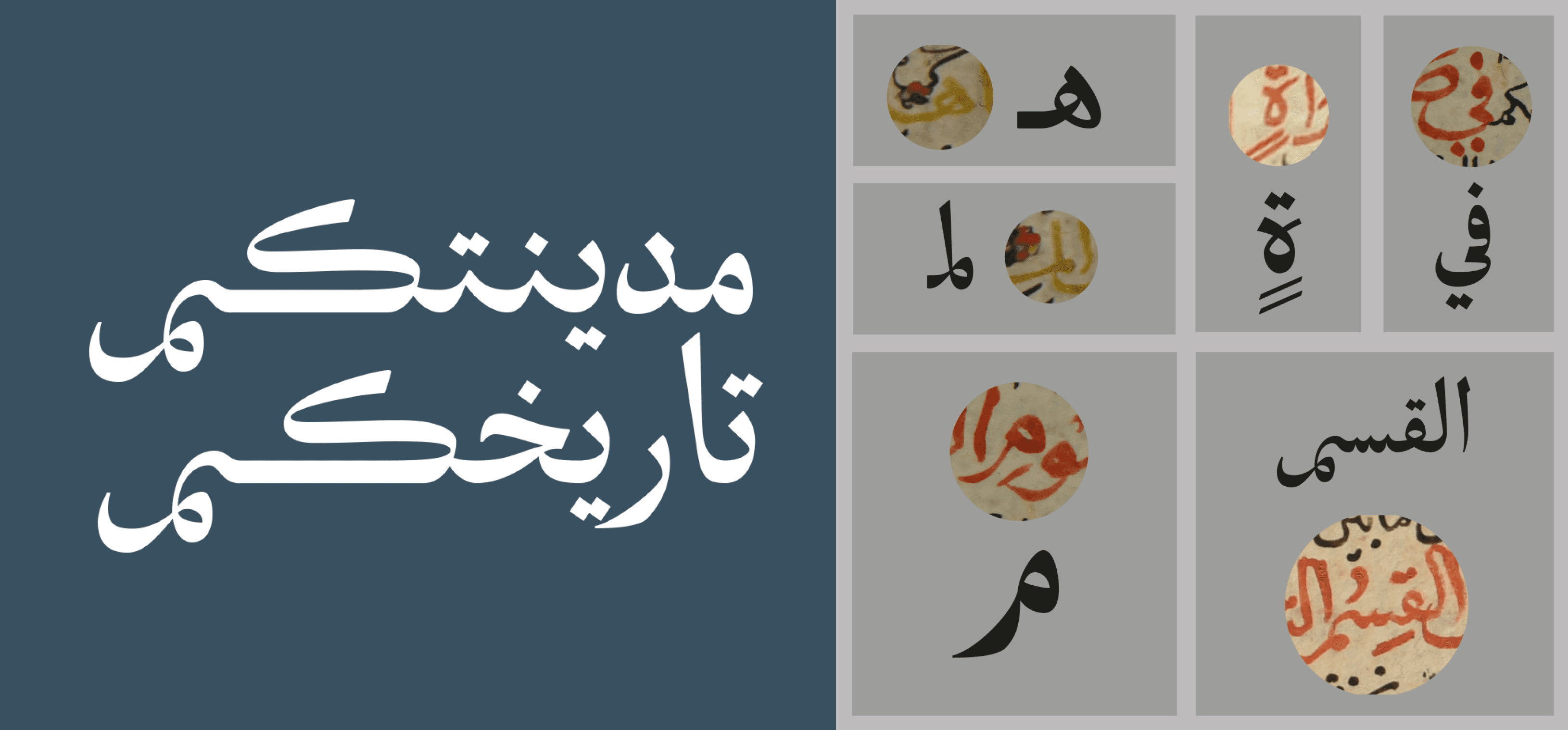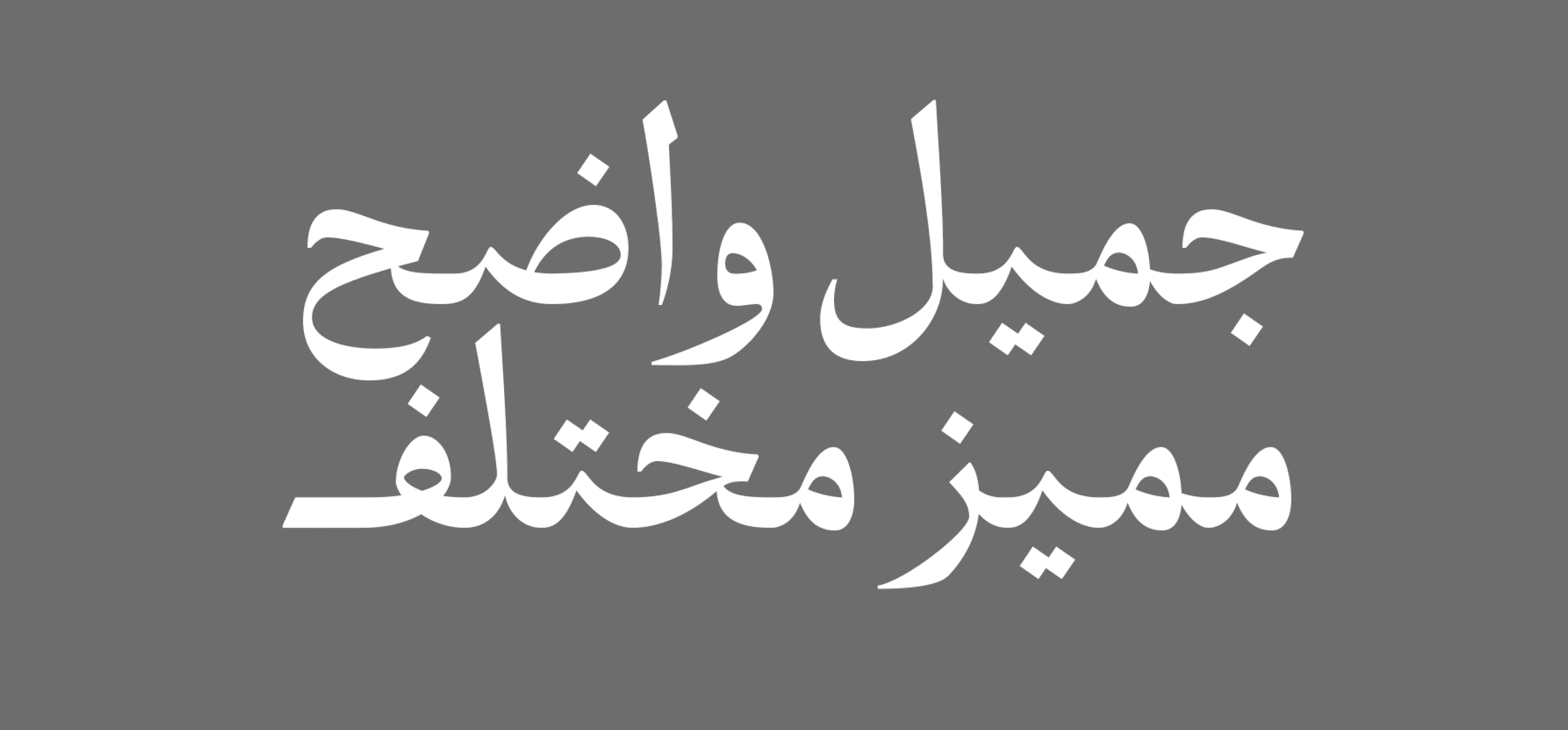
خط ثنائي اللغة صُمم خصيصًا لمدينة الدرعية في المملكة العربية السعودية من قبل مكتب Tarek Atrissi Design.
يمثل الخط الهوية البصرية الرسمية للمدينة، ويعكس تراثها العريق الذي يُعد مهد الدولة السعودية.
يجمع التصميم بين الطابع التراثي والأناقة العصرية، مستلهمًا من عمارة الدرعية التقليدية ومعالمها التاريخية مثل حي الطريف المدرج ضمن قائمة اليونسكو.